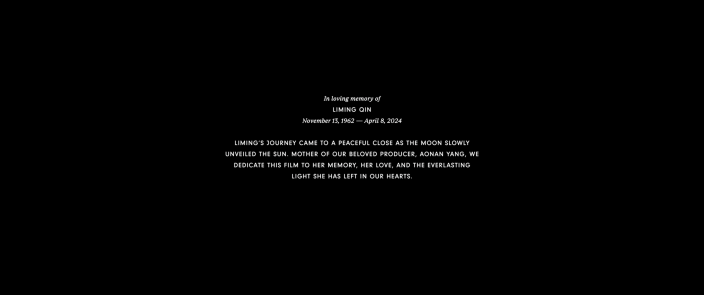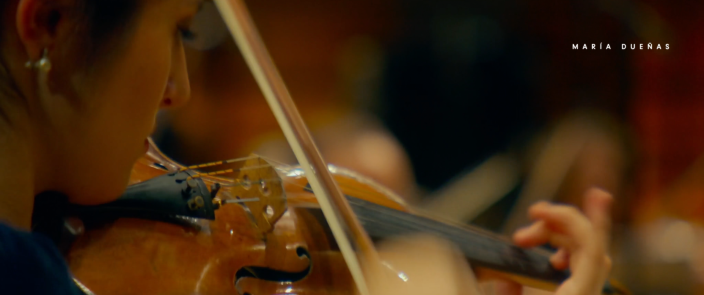
Measures for a Funeral
Measures for a Funeral beleuchtet auf brillante Weise die Annäherung einer jungen Akademikerin an eine Frau — die gefeierte kanadische Geigerin Kathleen Parlow aus dem frühen 20. Jahrhundert — während sie gleichzeitig vor einer anderen flieht, ihrer gescheiterten Musikerin Mutter.
Die Titelgestaltung nimmt die Musikalität und Bewegung des Filmes auf. Wobei die subtile Animation des Haupttitels dies noch einmal verstärkt. Die Credits am Ende erinnern an Notenpapier und untermalen in dieser weise ebenso das Thema des FIlms.
Schrift: Rhetorik Serif von AllCaps & Neuzeit Grotesk von Wilhelm Pischner